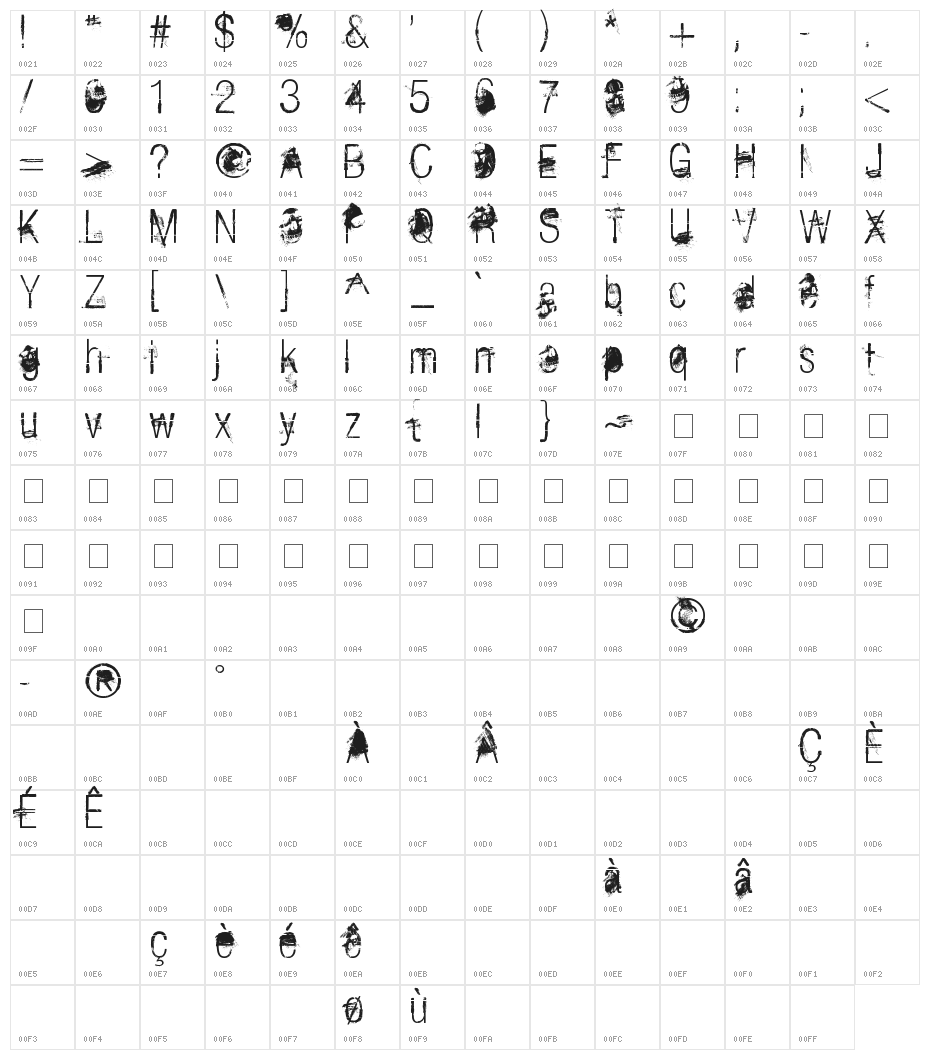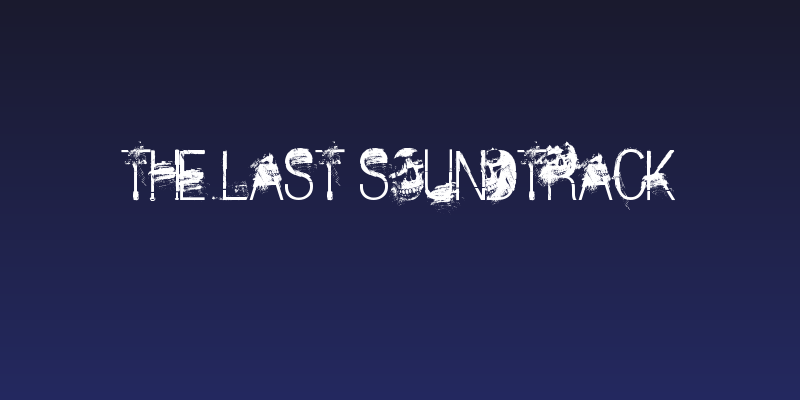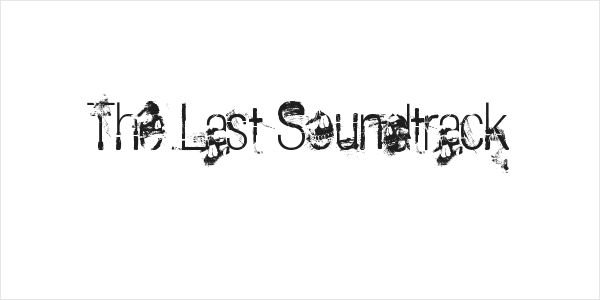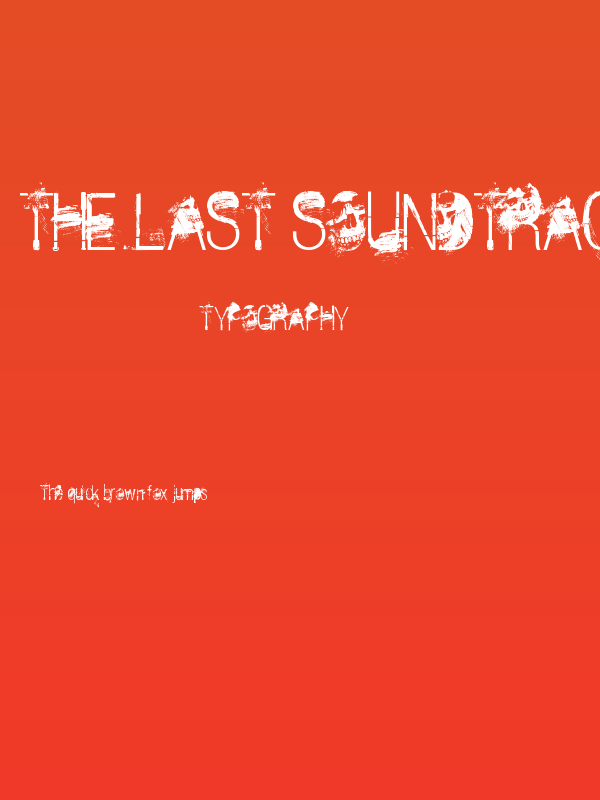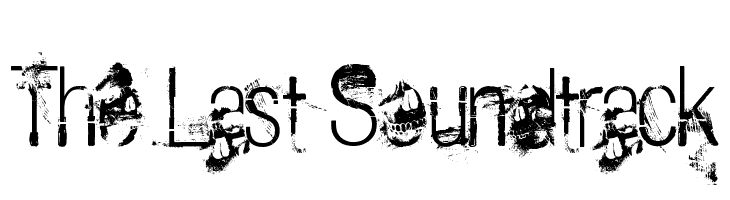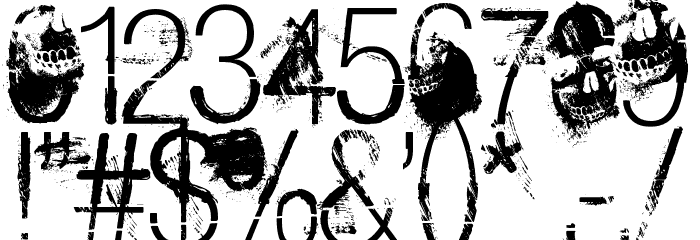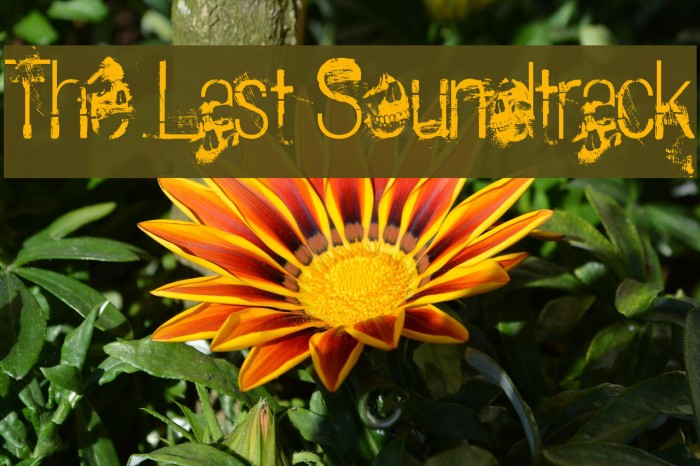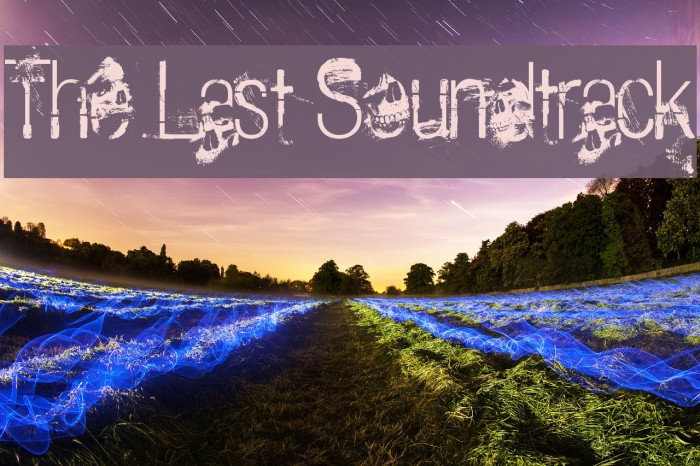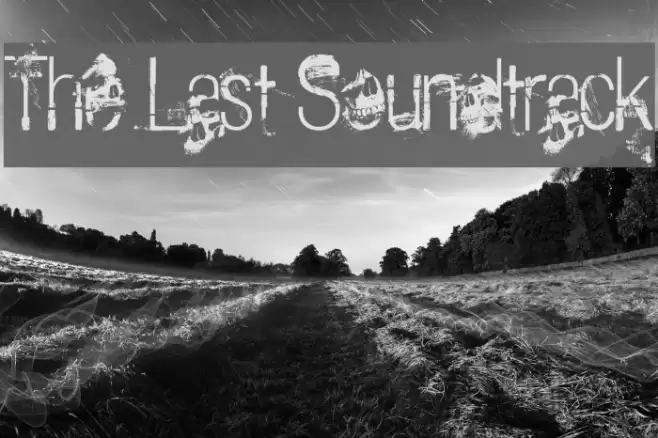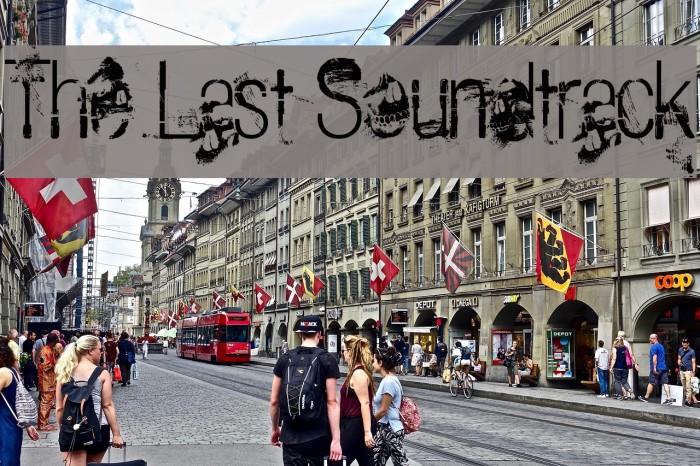
The Last Soundtrack Font
✎ Distorted Eroded
| Gesamtstil | Grunge, Edgy, Alternative |
| Anwendungsfall | Logos, Posters, Album Covers |
| Vorgeschlagene Projekte | Ideal for music album covers, horror movie posters, edgy apparel designs, and alternative event flyers. |